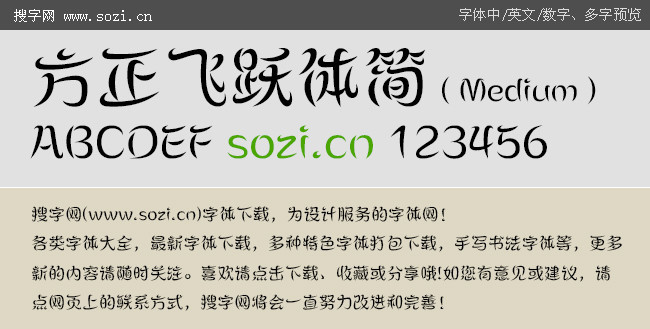
方正飛躍體簡Medium
搜字網(wǎng)提供一款方正飛躍體簡中文字體下載,方正飛躍體簡是一款充滿活力和跳躍的中文字體,該字體特點(diǎn)是沒有直線,全是弧線組成,橫劃都向右上角斜上,頭部有一個(gè)彎鉤,所有撇,捺,點(diǎn)都用弧線形表達(dá),因此增強(qiáng)飛躍體的感覺,適合應(yīng)用于包裝設(shè)計(jì)、平面設(shè)計(jì)、網(wǎng)頁設(shè)計(jì)、海報(bào)設(shè)計(jì)等應(yīng)用。